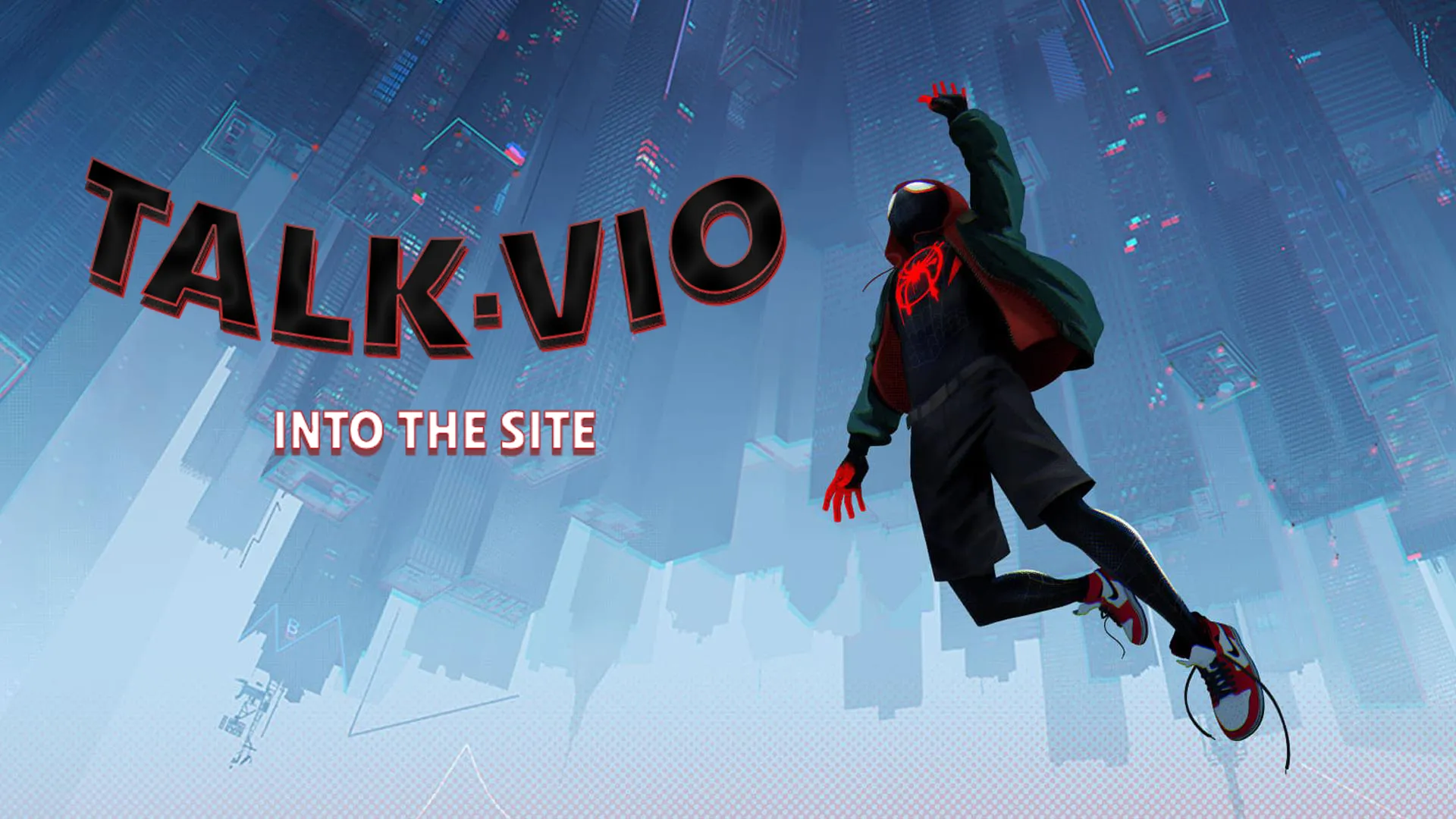
Последняя на сегодня «talkvio-обработка» посвящена мультфильму «Человек-паук: Через вселенные».
Это тот пример, когда от шрифта тут мало что осталось.
Взяв за основу достаточно простой шрифт «Veto Sans» создатели его обработали так, что выглядит он просто превосходно. Им выполнены все надписи на промо-постерах и рекламных баннерах к фильму, а также его можно встретить в самом мультфильме.